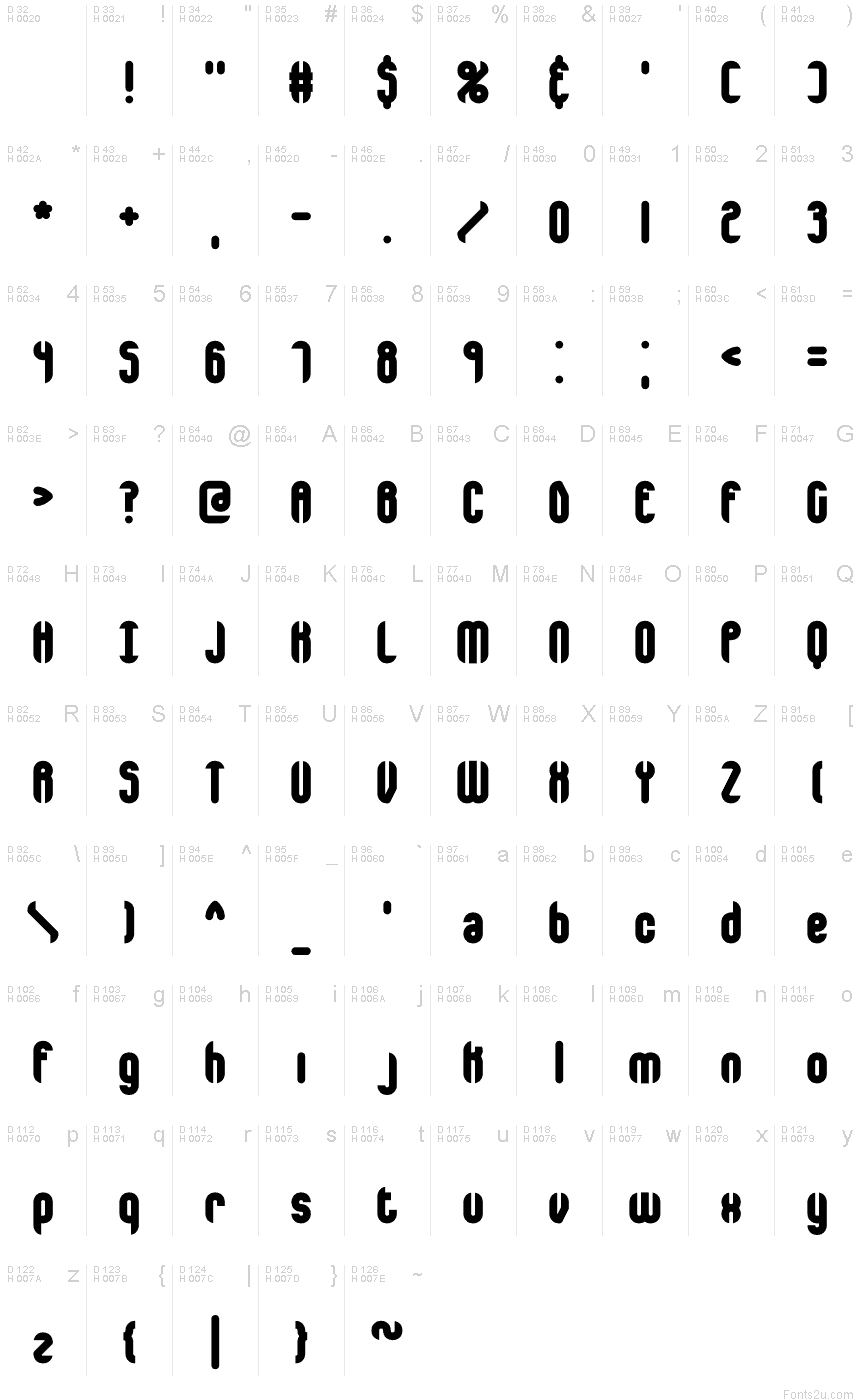
Encapsulate Plain BRK od ÆNIGMA FONTS to nowoczesny, dekoracyjny krój pisma. Masywny, o miękkich krągłościach i wyraźnych, pionowych nacięciach, dzięki którym każde słowo wygląda jak odciśnięte w świeżym tuszu. Jest odważny, ale nie sztywny – kapsułowe kształty nadają mu zabawny, zwarty rytm.
Encapsulate Plain BRK sprawdza się na logotypach, plakatach, naklejkach, etykietach, miniaturkach YouTube, ulotkach, grafikach na merch czy ekranach powitalnych aplikacji, gdzie liczy się natychmiastowy efekt. Użyj go w dużym rozmiarze, z szerokim kerningiem, aby pozwolić zaokrąglonym formom „odetchnąć”. W tekście głównym postaw na neutralny bezszeryfowy krój, aby nagłówek zachował swój wyrazisty charakter.
Encapsulate Plain BRK